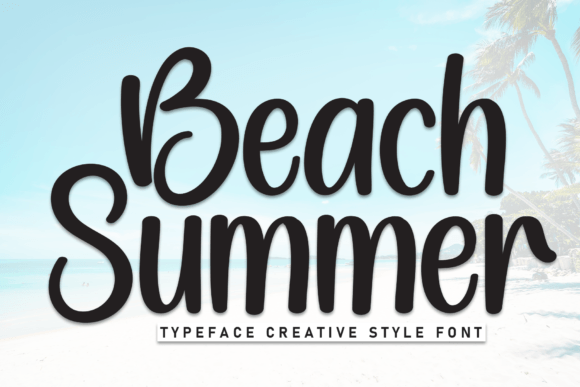
Beach Summer
Ulasan Lengkap Font Beach Summer – Sentuhan Kasual yang Menghangatkan Desain Anda
Jika Anda sedang mencari font casual handwritten yang mampu menambah kesan hangat dan bersahabat pada setiap proyek kreatif, Beach Summer adalah pilihan yang tepat. Dengan goresan melengkung yang playful, font ini memberi nuansa santai sekaligus mudah didekati, cocok untuk undangan pribadi, grafik media sosial, serta desain estetika yang memerlukan sentuhan tangan yang lembut.
Keunggulan Utama Beach Summer
- Gaya Hand‑drawn yang Menawan – Setiap huruf tampak seperti ditulis dengan pulpen berwarna pastel, menambah kesan whimsical yang sulit ditolak.
- Stroked Rounded & Playful – Bentuk melengkung memberikan rasa ramah dan mengundang, ideal untuk brand yang ingin tampil humanis.
- Fleksibilitas Penggunaan – Cocok untuk undangan pernikahan pantai, poster event musim panas, atau posting Instagram yang ingin menonjol.
- Keterbacaan Tinggi – Meskipun bergaya tulisan tangan, ukuran dan jarak antar huruf tetap terjaga, sehingga teks tetap jelas dibaca.
Kenapa Beach Summer Cocok untuk Proyek Pribadi?
Sentuhan hangat dan santai dari Beach Summer membuatnya sangat cocok untuk proyek yang ingin mengekspresikan keakraban dan kebahagiaan. Baik Anda membuat kartu ucapan, flyer liburan, atau thumbnail YouTube, font ini akan menambah nilai emosional yang kuat dan meningkatkan tingkat engagement audiens.
Kesimpulan
Beach Summer bukan sekadar font tulisan tangan; ia adalah ekspresi visual yang menyebarkan keceriaan musim panas ke setiap desain. Dengan gaya rounded, playful, dan mudah dibaca, font ini menjadi solusi sempurna untuk siapa saja yang menginginkan tampilan ramah, hangat, dan profesional dalam satu paket. Unduh sekarang dan biarkan karya Anda berjemur dalam sinar kreativitas!